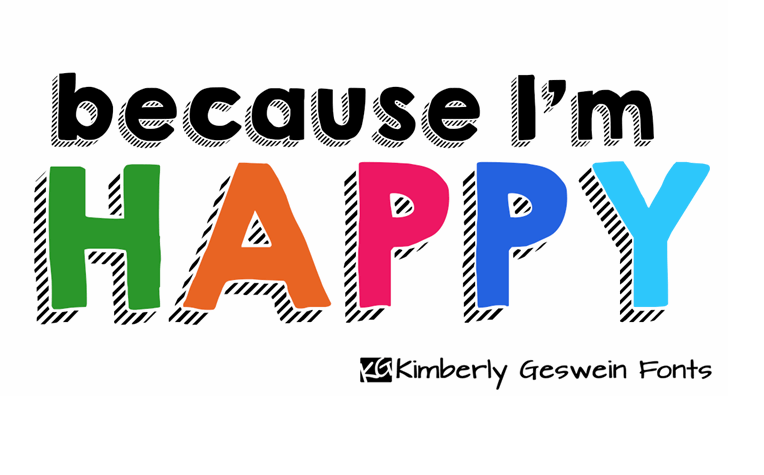
A Font ‘KG HAPPY’ é perfeitamente indicada para quem procura uma aparição alegre e moderna na sua próxima arte digitizada. Desenhada pelo designer Hamilton, esta font é ideal para criar um estilo de gráficos que lembram as artes chockboard contemporâneas, com suas cores vibrantes e estilo retro moderno. Ideal para quem busca uma maneira única de trazer um toque de frescor a seu design, essa font pode ser usada tanto para textos individuais quanto para estilos arco-íris. Para alcançar o máximo dessa versatilidade, é possível criar camadas em diferentes cores e tonalidades que se sobrepõem, criando uma aparência tridimensional que adiciona profundidade ao seu design. Com sua facilidade de uso e estilo alegre, a ‘KG HAPPY’ oferece um lembrete perfeito da versatilidade do design moderno e da importância de manter o espírito fresco. Seja você designer ou criador de conteúdo digital, este é um elemento que certamente irá enriquecer sua composição visual, apresentando uma harmonia entre a simplicidade das artes chockboard e os tons vibrantes do design contemporâneo.